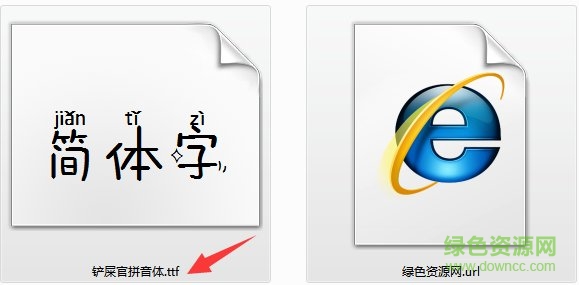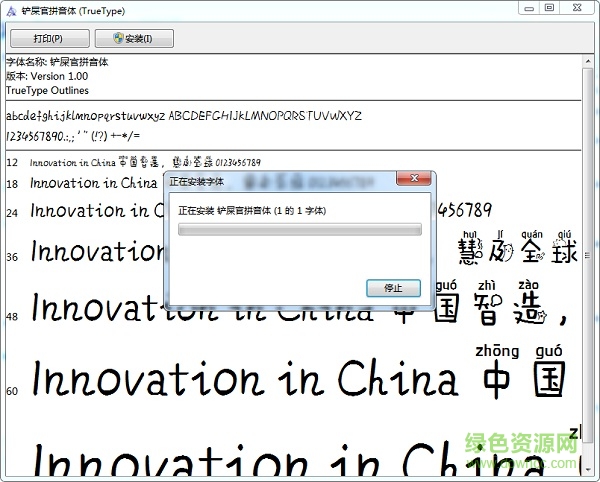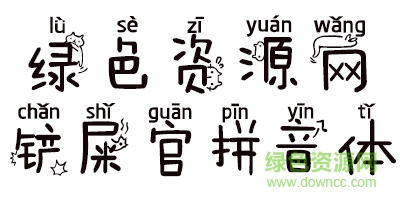
鏟屎官拼音體是一個很萌的拼音字體。每個字體上都有一只小貓咪,讓字體看上去更加生動有趣。使用這款字體設計一些兒童類海報再好不過了。喜歡的小伙伴快來綠色資源網下載使用吧。
鏟屎官拼音體不僅有著標準的拼音注釋,而且還增加了可愛的愛心符號,讓文字更加活潑,充滿愛心!。適用于那些個性十足的海報、廣告等方面,也可以用于一些早教的場景。適用范圍非常廣泛!